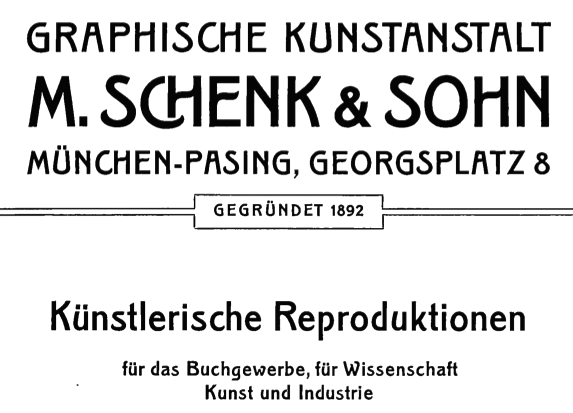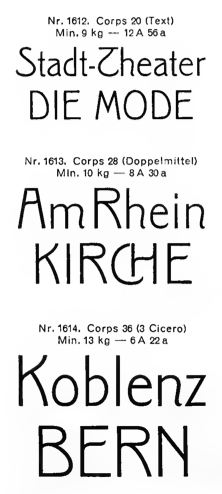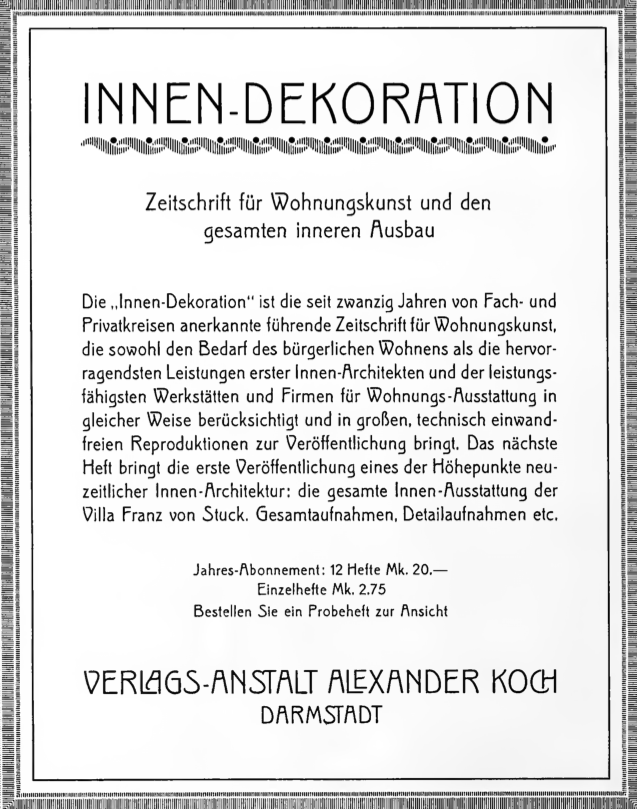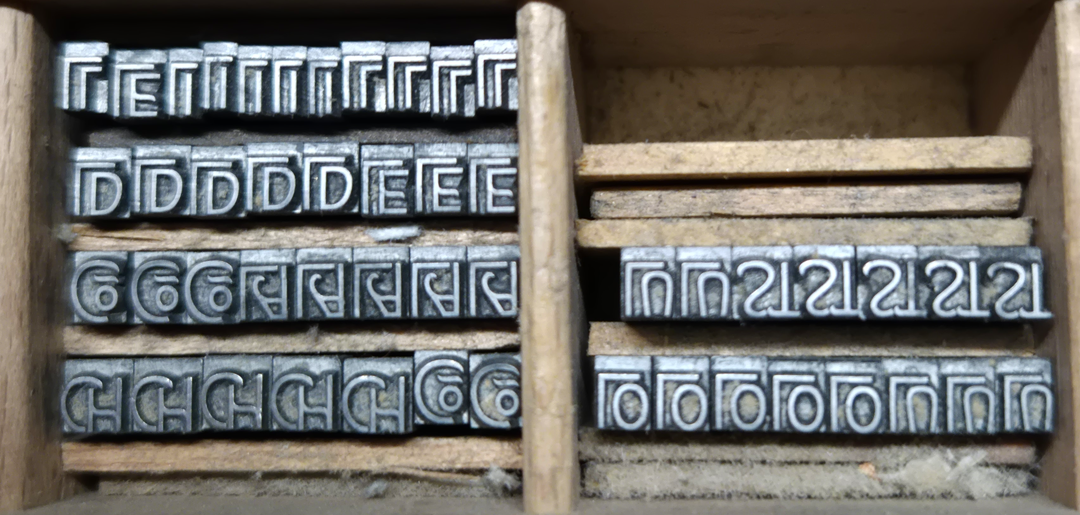
Bestimmung einer Jugendstilschrift (Handsatz). Wer kann helfen ?
wer kann bei der Bestimmung der nachfolgend gezeigten Jugendstilschrift helfen?
Leider ist mir praktisch nichts zur Herkunft/ Zuordnung bekannt. Es handelt sich um eine Handsatzschrift in deutscher Normalhöhe. Sie war eingelagert und vergessen in einem kleinen Setzkasten mit französischer Beschriftung.
Andruck und ein Foto der Versal-Ligaturen anbei.